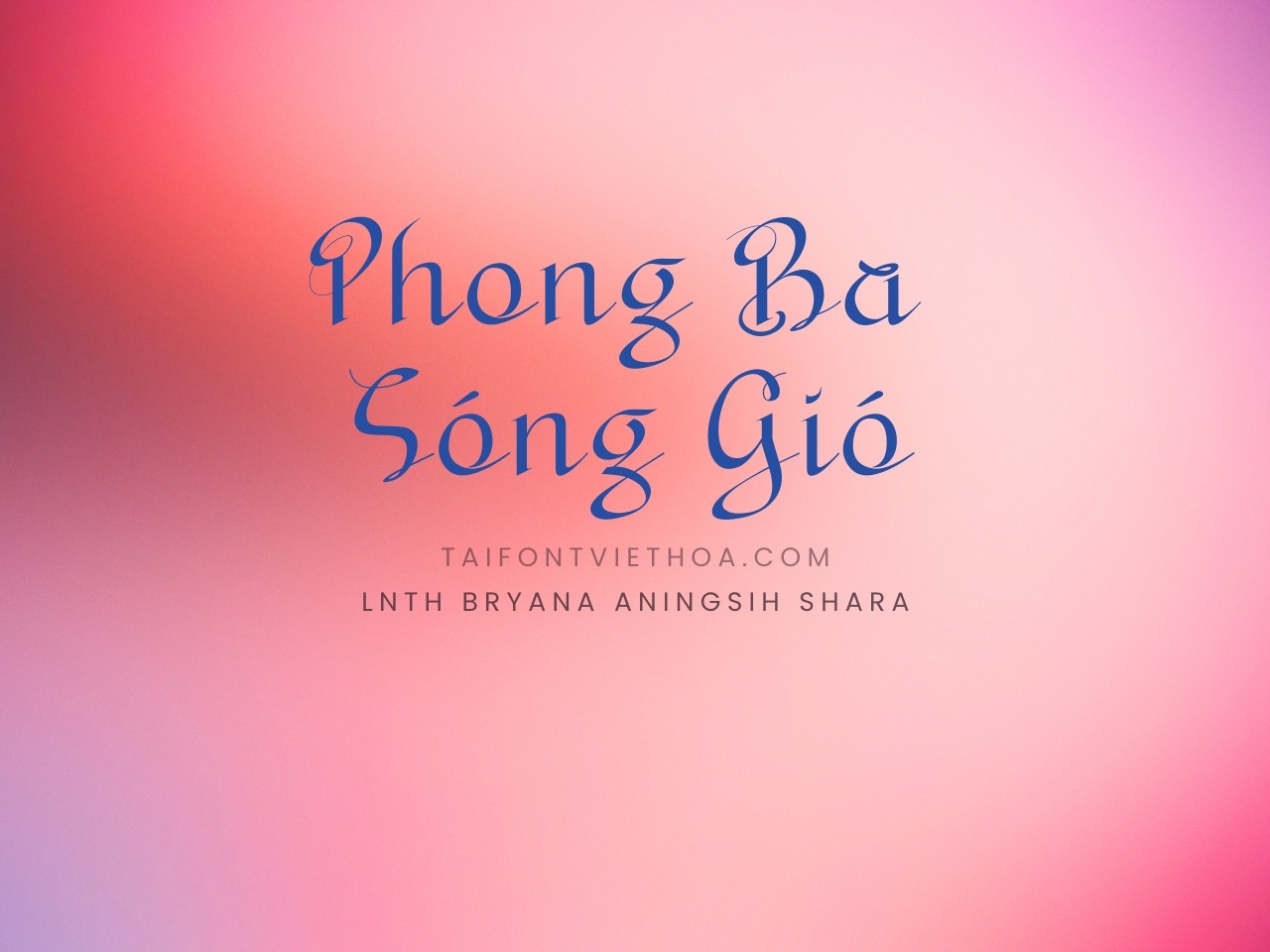
Font việt hóa LNTH Bryana Aningsih Shara
Giới thiệu về font Bryana Aningsih Shara
Bryana Aningsih Shara là một font script mềm mại và nữ tính, được thiết kế bởi Aningsih – nhà thiết kế chuyên về các kiểu chữ viết tay, hiện đại và thanh lịch. Font mang đến phong cách lãng mạn, đầy uyển chuyển với những đường nét thanh mảnh và các đuôi chữ kéo dài quyến rũ. Phiên bản Việt hóa được thực hiện bởi Tuỳn Pucca, hỗ trợ đầy đủ dấu tiếng Việt cùng hơn 80 ngôn ngữ khác, đảm bảo tính linh hoạt cao cho các dự án thiết kế đa ngôn ngữ và đa văn hóa.
Font này đã được taifontviethoa.com tuyển chọn và chia sẻ đến cộng đồng yêu font script tinh tế. Với chất lượng Việt hóa chuẩn chỉnh và phong cách thẩm mỹ cao, Bryana Aningsih Shara đã được ứng dụng rộng rãi trong thiết kế thiệp mời, thương hiệu mỹ phẩm, logo cá nhân, và các sản phẩm mang tính nghệ thuật nhẹ nhàng, bay bổng.
Đặc điểm thiết kế và ứng dụng của font Bryana Aningsih Shara
Bryana Aningsih Shara nổi bật với các đường cong mềm mại, độ tương phản nét thanh – nét đậm vừa phải, tạo nên cảm giác viết tay uyển chuyển và sang trọng. Các ký tự được kết nối tự nhiên nhờ hệ thống ligatures linh hoạt, giúp văn bản hiển thị liền mạch và duyên dáng. Swash mở rộng ở đầu hoặc cuối chữ tạo điểm nhấn thị giác và mang tính cá nhân hóa cao.
Font rất phù hợp với các ứng dụng như: thiết kế thiệp cưới, bao bì mỹ phẩm, logo thương hiệu thời trang nữ, typography nghệ thuật, thiết kế bìa sách, và truyền thông mạng xã hội mang sắc thái nhẹ nhàng. Các ngành nghề phù hợp gồm: spa, cưới hỏi, thời trang, mỹ phẩm, sáng tạo nghệ thuật và quảng cáo cao cấp.